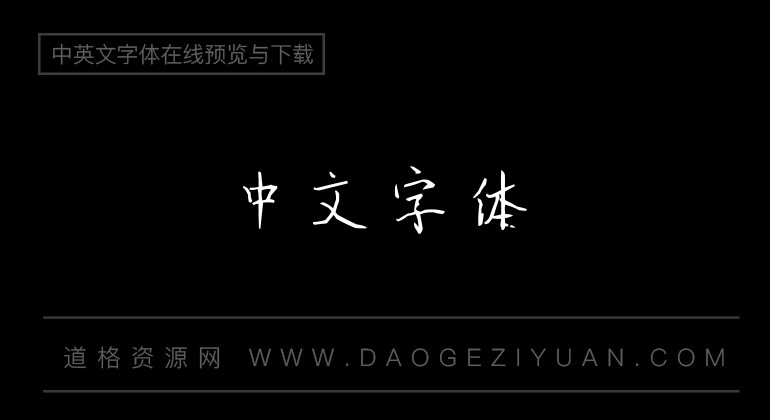
张建宇体是由张建宇先生设计的一种中文字体,它于1985年初步完成,并于1988年正式发行,是一种具有良好的可读性和易用性的汉字字体。 张建宇体字体以“简洁、清新、大气、端庄”为设计理念,在汉字字体设计中,张建宇体以其独特的风格,拥有清晰的线条,柔和的笔画,优美的曲线,深厚的文化底蕴,在汉字字体设计中,拥有极高的地位。文件名:ZhangJianYuTi-1.ttf
张建宇体是一款非常不错的手写艺术字体,具有很好的视觉感,适合于文化类的宣传设计、商业类品牌的广告和产品包装设计以及个性化文字排版等较多场景。